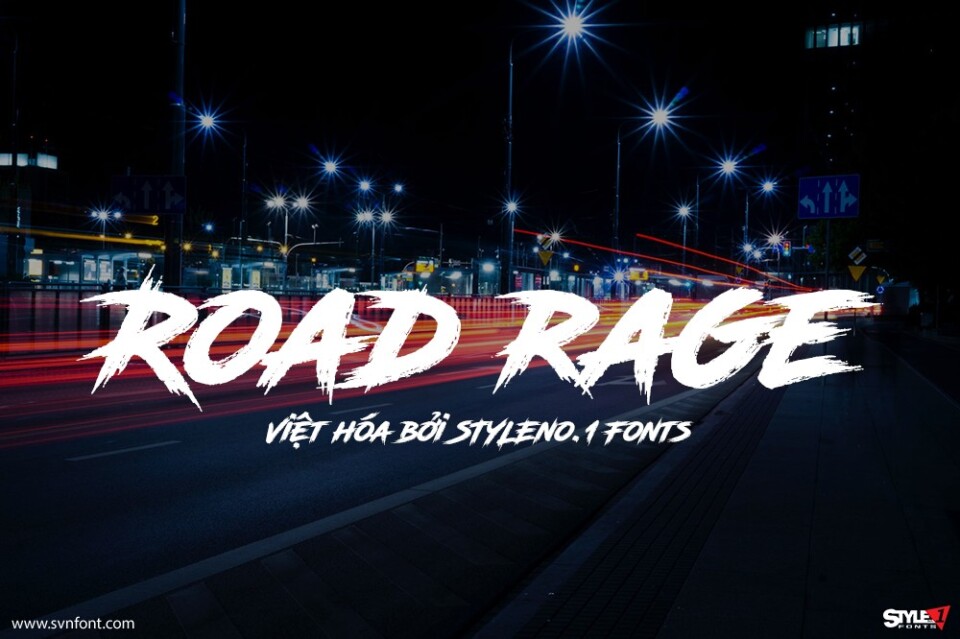
Giới thiệu về Font Việt hóa SVN Road Rage – Brush
Trong thế giới đồ họa, việc tìm kiếm một bộ Font Miễn Phí chất lượng luôn là ưu tiên hàng đầu của các bạn học sinh và giáo viên. Font Việt hóa SVN Road Rage – Brush là một cái tên nổi bật mang phong cách nghệ thuật đường phố đầy cá tính. Được thiết kế dựa trên nét vẽ cọ (brush) mạnh mẽ, bộ font này mô phỏng những đường nét thô mộc, dứt khoát và tràn đầy năng lượng. Đây là lựa chọn hoàn hảo cho các dự án yêu cầu sự phá cách, giúp thông điệp của bạn trở nên ấn tượng và khác biệt hơn bao giờ hết.
Đặc điểm nổi bật của Font Việt hóa SVN Road Rage – Brush
Phong cách Brush độc đáo
Điểm thu hút nhất của Font Việt hóa SVN Road Rage – Brush chính là những vệt mực lem tự nhiên, tạo cảm giác như được vẽ tay trực tiếp. Các ký tự có độ tương phản cao, nét dày mỏng đan xen tạo nên hiệu ứng thị giác mạnh mẽ. Điều này rất phù hợp để thiết kế tiêu đề báo tường, bìa sách hoặc các biểu ngữ sự kiện tại trường học.
Khả năng tương thích tốt